刚劲有力的字体可谓是平面设计必备的,广泛应用在招牌、logo、包装设计等设计领域。醒目又美观,字体的线条和结构安排合理,字形有棱有角。一般这种字体造型较于规整字形清晰易于看图找字,富于力度,给人以简洁爽朗的现代感,有较强的视觉冲击力,这种个性的字体,更适合于机械科技等主题。
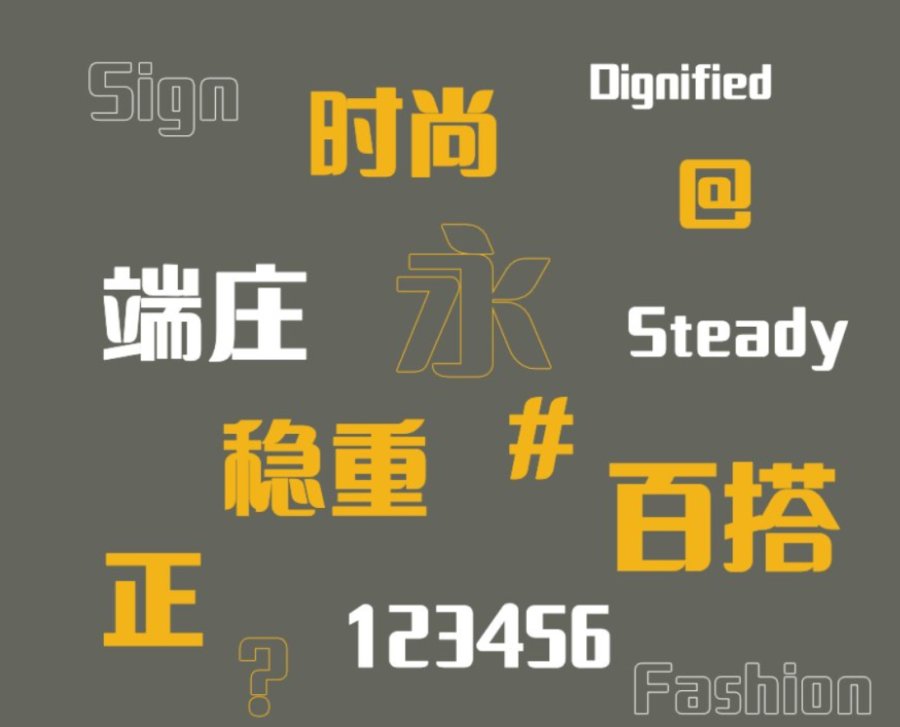
印品招牌体:这款招牌体字笔画粗壮,略带有纤细笔触,字形紧聚,但不失美感。在弯钩处都作了一点线条处理,看起来不那么死板。它的一撇一捺像极了柳絮飘飘。即便放于手机中阅读也不会产生视觉突兀,给人以浑厚有力的感受。
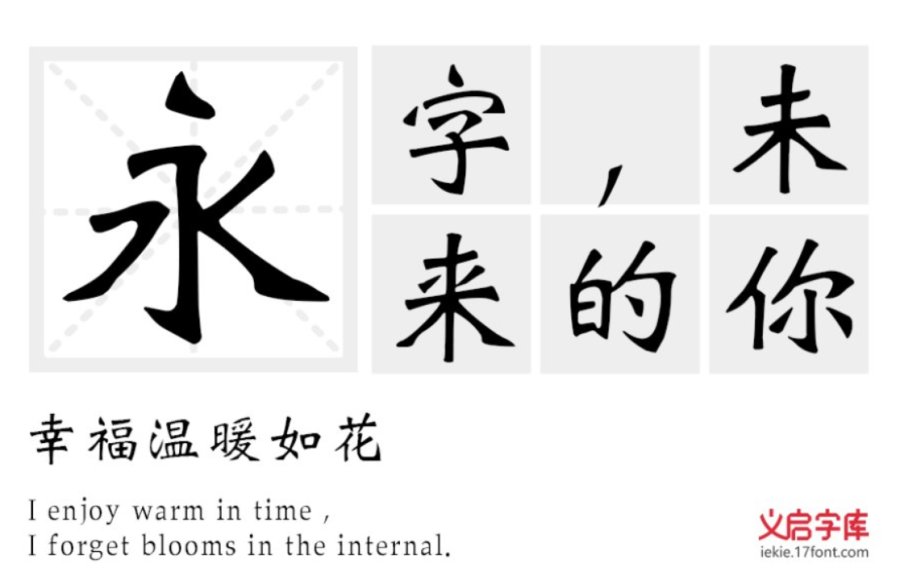
义启魏碑体:魏碑包括很多种,但是魏碑的笔画特点基本一致、结构有方有扁、章法间距差距不大。义启魏碑体,是一款融合性很高的魏碑。融合兼顾所有魏碑特性,大量吸收了石刻、摩崖、墓志铭等碑帖特性。起笔方圆并济,撇捺加重刀切感。整体重心内敛,字字精神充满张力。
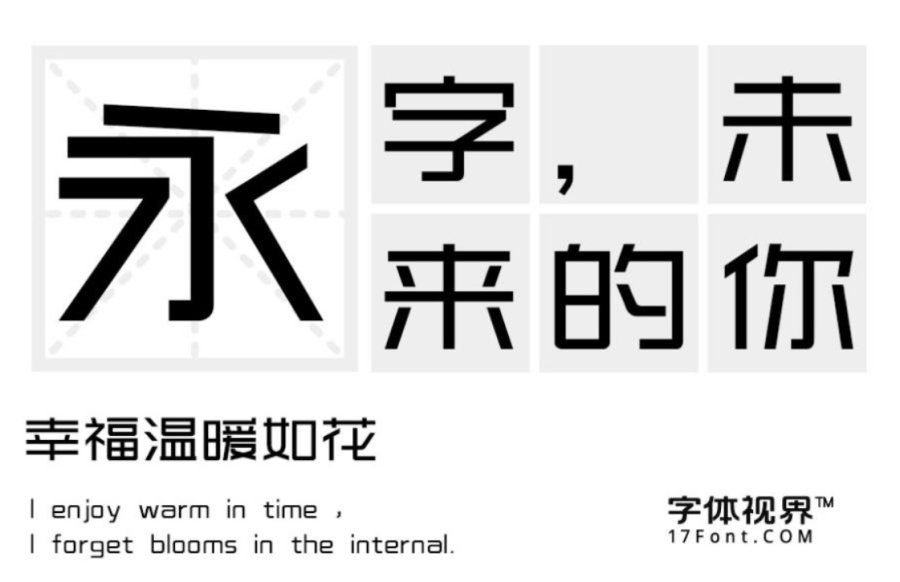
上首时尚体:这是一款无衬线字体,这类字体除本身文字的比划之外缺少装饰性的元素,风格较简约。整体风格时尚简洁又不失大气,字体笔画竖折处做圆角处理。整体特征坚硬、有力;具有现代、国际化的指向性,剔除过去人们陈旧的审美,取而代之的是更为现代的视觉风格。适用于高端的商业广告、商业标语、电子产品等多途定位。